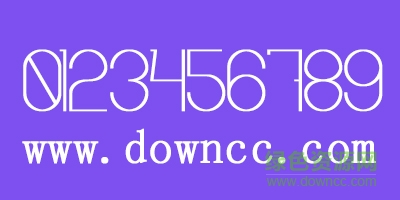
veribest gerber 0字體是一款常常用來(lái)設(shè)計(jì)條形碼數(shù)字信息的條形碼字體應(yīng)用!這款字體的特點(diǎn)就是打出的”0“數(shù)字中會(huì)有一個(gè)明顯的斜杠杠,設(shè)計(jì)的數(shù)字比較美觀(guān)。歡迎需要的朋友來(lái)綠色資源網(wǎng)下載食使用。